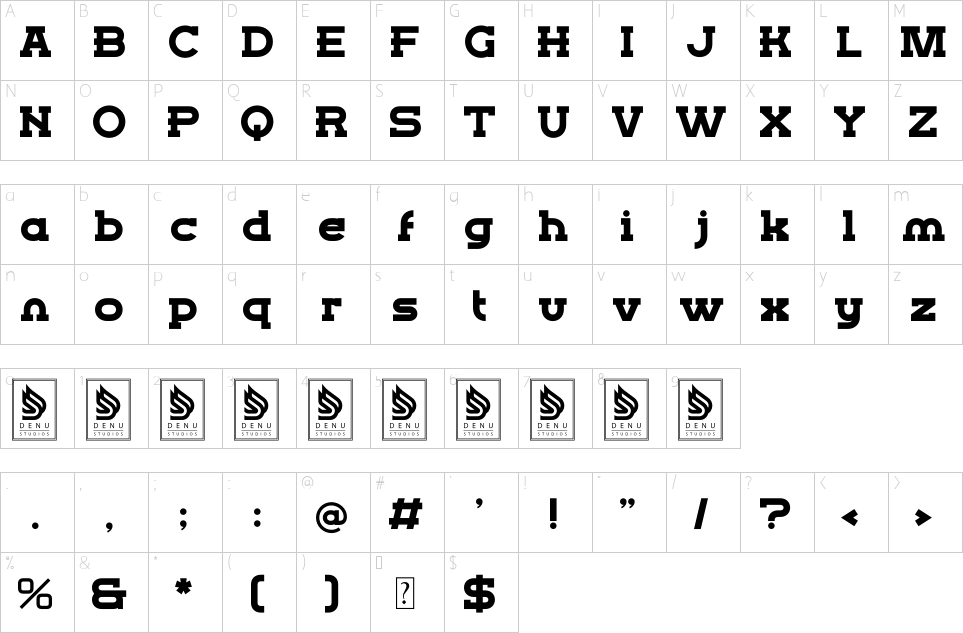
Aqui está uma descrição em português para a página de download da fonte ‘Angkor Strat Font’: A fonte ‘Angkor Strat’ é uma escolha perfeita para quem busca uma fonte moderna e elegante para usar em projetos de design gráfico. Desenvolvida por Denustudios, esta fonte foi projetada para oferecer uma estética minimalista que combina bem em qualquer layout. Com uma excelente legibilidade e variedade de opções de peso, ‘Angkor Strat’ é uma excelente opção para criar designs que destacam a legibilidade sem comprometer a beleza do texto. Com 334 downloads, é fácil ver que a fonte é apreciada por muitos designers. Se você está procurando por uma fonte de alta qualidade para seu próximo projeto, ‘Angkor Strat’ é uma fonte que merece uma olhada.